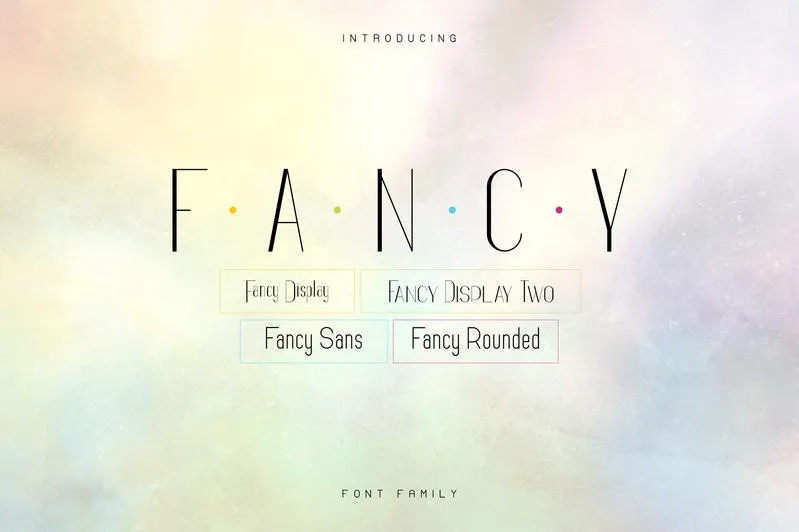
Fancy Font Family – 12 Fonts – Download Grátis
A Fancy Font Family é uma família de fontes limpa e moderna que inclui 12 diferentes tipos, todas aptas para suporte multi-língua. Estas fóruns são versáteis e perfeitamente adaptáveis tanto para aplicação em grandes tamanhos quanto para fontes menores e detalhadas. Suas linhas finas e sua tipografia limpa tornam-a ideal para uso em design gráfico, publicidade ou qualquer outro tipo de projeto visual que necessite de uma aparência sofisticada e moderna. Não importa o tamanho da área que você estiver trabalhando, a Fancy Font Family mantém seu profissionalismo e elegância, garantindo um resultado impecável em sua próxima arte digital. Ideal tanto para designers quanto para os amantes do design gráfico, esta família de fóruns é perfeita para tornar seus projetos ainda mais impressionantes.